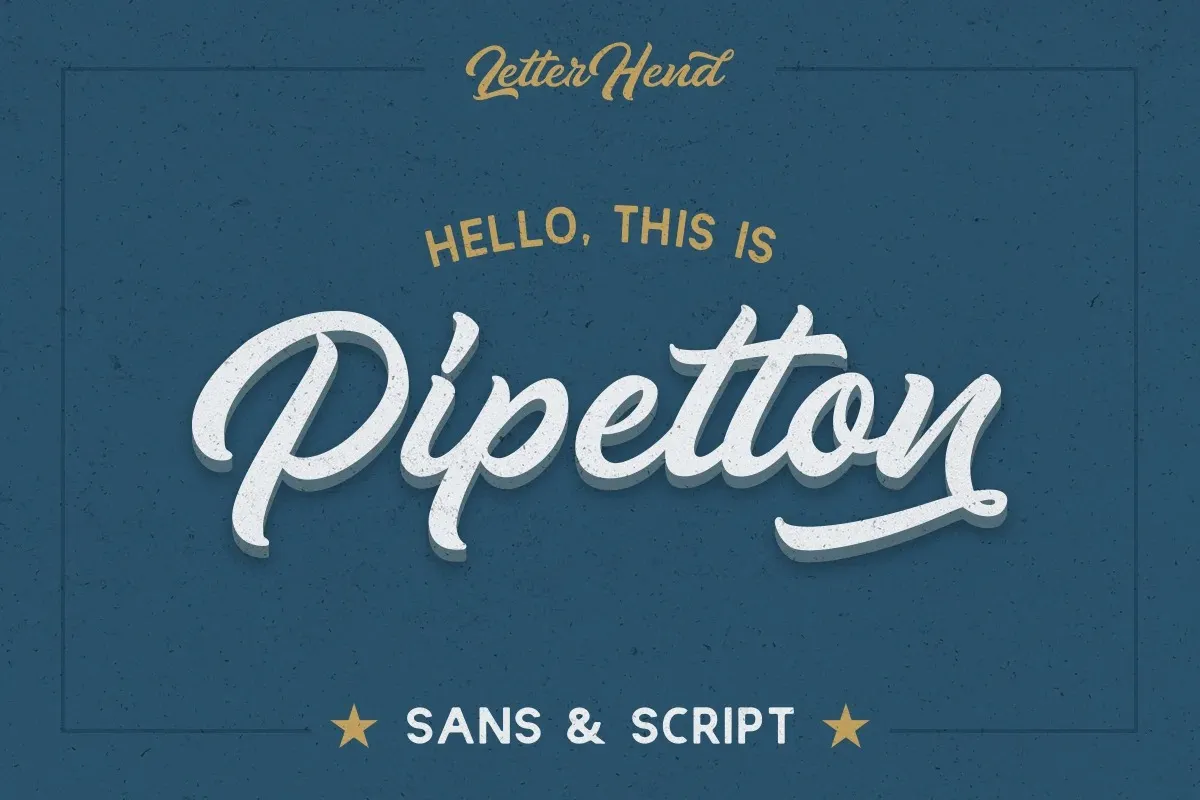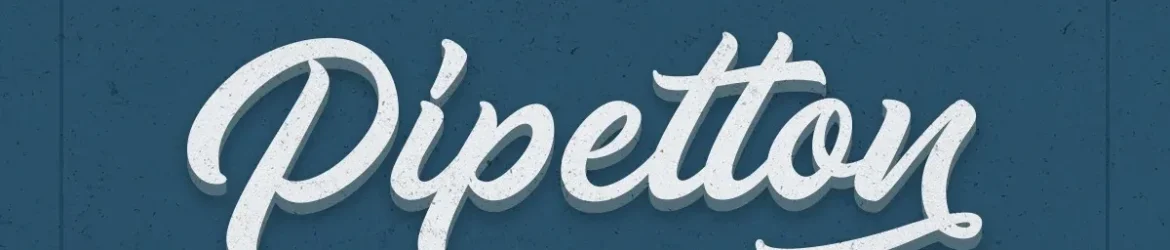
A Pipetton Font é uma tipografia script que inspira-se nos estilos do final dos anos 90. Ela traz os melhores elementos deste período artístico e dá vida a uma fonte de escrita com traços marcantes e elegante, perfeitamente complementada por um tipo sans-serif. Esta tipografia vem em versões maiúsculas e minúsculas, incluindo as pontuações e símbolos necessários para torná-la completa. Suas letras únicas e bold tornam-na ideal tanto para logotipos quanto para marcas de marca ou rótulos de produtos. A Pipetton Font é perfeita para qualquer aplicação visual que exija uma tipografia chamativa, garantindo que ela se destaque e seja memorável. Ela oferece alternativas estilizadas, conjuntos ligados e swashes, dando-lhe a liberdade criativa necessária para adaptar e personalizar sua fonte ao seu projeto específico. Com esta fonte no seu arsenal de recursos gráficos, você pode criar design visual impecável e singularmente diferenciado.